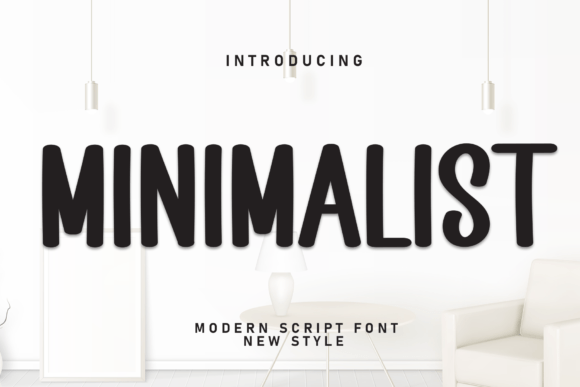
Minimalist
Minimalistのような高品質の素材をお探しの場合、このプレミアムパッケージはクリエイティブなプロジェクトに素晴らしい選択です。
精密に作られたMinimalistは、クリーンなベクター、滑らかなタイポグラフィ、そして安心のための商用ライセンスを提供します。
POD(オンデマンド印刷)製品、結婚式の招待状、またはソーシャルメディアのグラフィックを作成している場合でも、Minimalistは理想的です。